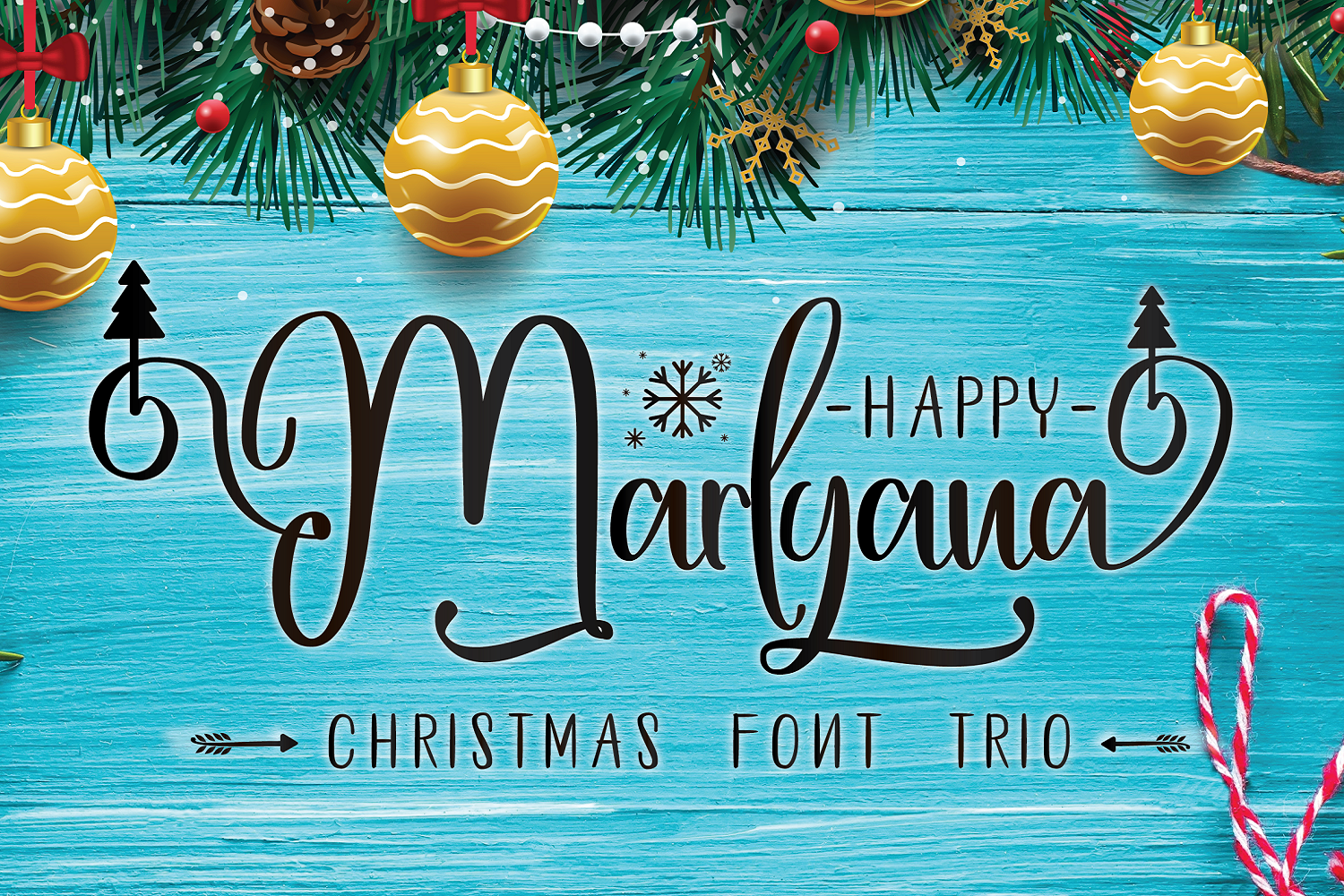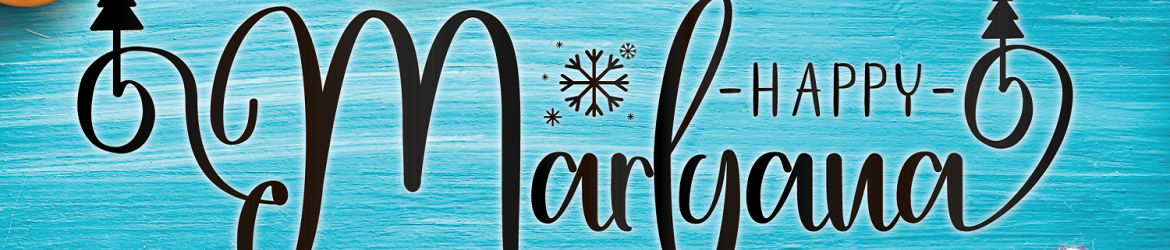
Happy Marlyana Font Trio – Download Grátis
A “Happy Marlyana Font Trio” é uma nova fonte escrita à mão com três estilos variados que trazem uma sensação deliciosa e harmônica. Este conjunto único é perfeito para aqueles que buscam um toque de suavidade em seus trabalhos gráficos, seja para cartões de boas-vindas, materiais de marca, cartões de visita, frases inspiradoras ou até mesmo para posters. A fonte “Happy Marlyana Font Trio” traz uma atmosfera leve e encantadora, ideal para aqueles que querem transmitir emoções alegres em seus projetos. Seja você um designer gráfico, um profissional de marketing ou simplesmente alguém que deseja dar um toque especial em suas criações, essa fonte é uma escolha inteligente. Sempre pronta para tornar sua arte mais divertida e encantadora.